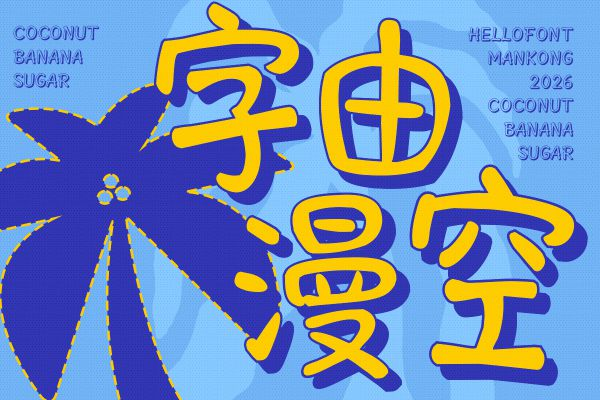
去哪下载适合动漫的字体,分享两种方法
做动漫设计或者同人创作的时候,最让人头疼的往往不是画技,而是找不到那种“对味儿”的字体。明明画面张力十足,配上标题后总觉得差点意思,要么太严肃,要么太普通,完全撑不起二次元那种热血、可爱或者神秘的氛围。到底适合动漫行业的字体去哪下载,才能既不侵权,又能精准表达出作品的情绪?本文给大家介绍两种下载适合动漫设计的字体的方法
通过字由下载动漫字体
对于设计师来说,字由它不仅仅是一个下载工具,更像是一个可以直接预览效果的灵感库。它的界面很干净,操作逻辑也很符合我们做图的习惯,不需要复杂的设置就能快速看到字体在画面中的样子。
字由中不错的动漫字体
字由拥有非常清晰的字体风格分类,可以在分类中选择“卡通”,进行动漫字体的筛选。
立即下载动漫字体字由漫空
字由漫空灵动、轻盈,带有一定的呼吸感,适合文艺、清新的设计,或者作为标题、副标题使用,能营造出一种浪漫、自由的氛围。
点字奇趣
点字奇趣充满趣味性,字形结构可能不那么规整,带有搞怪或童趣的色彩。适合儿童类产品、创意广告、Vlog 封面,能增加设计的活泼感。
字由飘带
字由飘带笔画末端或转折处带有类似丝带飘动的设计,流畅且富有动感。适合节庆贺卡、女性时尚品牌、剪彩或庆典类的主题设计。
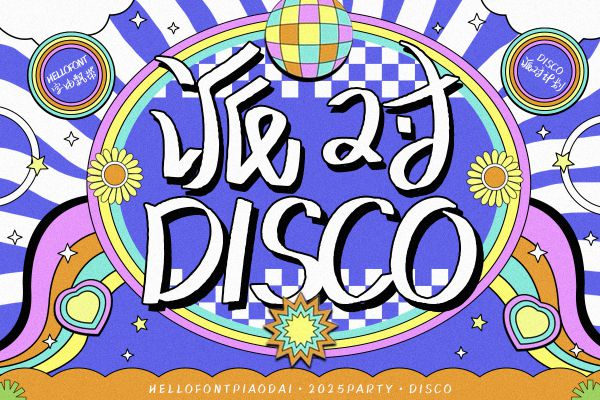
字由面包树
字由面包树属于“圆润体”或“萌系字体”,笔画粗壮饱满,像面包一样圆鼓鼓的。适合可爱风的设计、餐饮广告(尤其是甜点、烘焙类)、母婴产品。
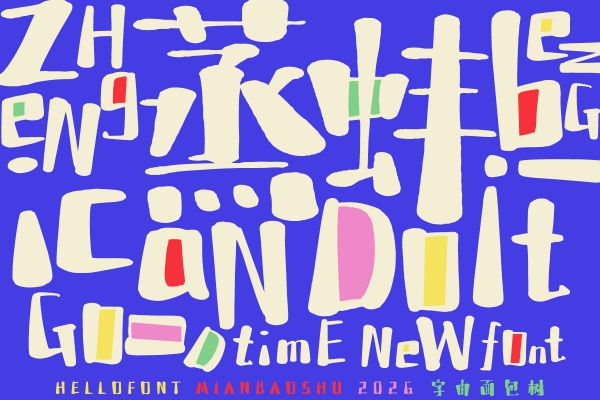
点字天然呆
点字天然呆具有手写感,字形看起来憨厚、简单,有一种“呆萌”和“无公害”的视觉效果。非常适合作为日常生活的 Vlog 字幕、心情语录或随性的插画配字。
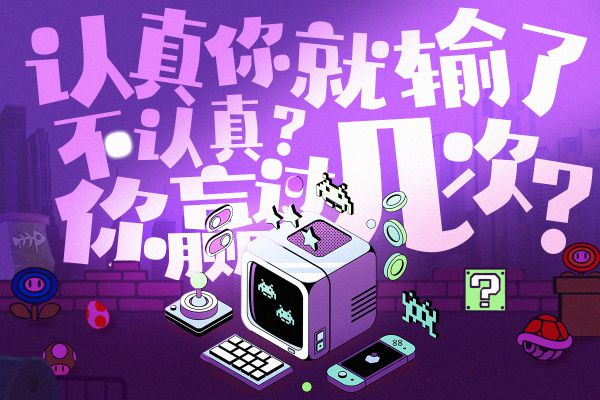
字由AI生成动漫字体
虽然现成的字体库已经很丰富了,但有时候我们做原创动漫IP,总觉得市面上的字体还是不够独特。大家都用那几款热门字体,作品容易显得同质化。更重要的是 AI 生成的动漫字体是可以免费商用的。
找字体其实和找素材一样,是动漫创作中绕不开的一环。与其每次都为了“适合动漫行业的字体去哪下载”而焦虑,不如收藏几个像字由这样靠谱的平台,平时多上去逛逛,积累自己的字体库。
无论是从现成的免费商用库里挑选,还是利用AI工具生成独特的专属字体,目的都是为了让我们的画面更有说服力。希望我分享的这些经验和资源,能帮你找到那款最能代表你作品风格的字体。